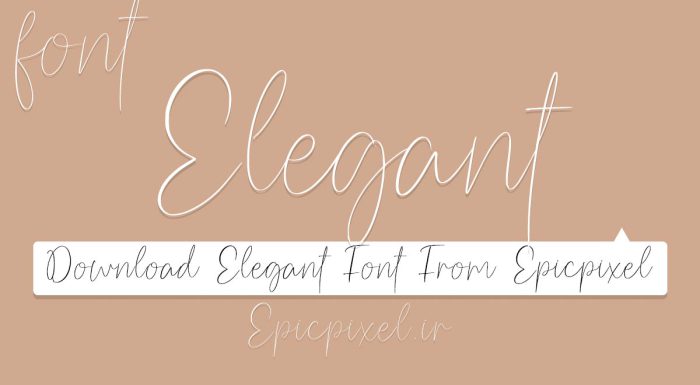
فونت Elegant انگلیسی
دانلود فونت Elegant انگلیسی Font الگانت |
| ⭐ مجموعه فونت | دانلود فونت انگلیسی الگانت Font Elegant |
| ⭐ توضیحات | الگانت یک قلم دست نویس بسیار نرم و تمیز است که بسیار فریبنده است و توجه بسیاری از افراد را به خود جلب می کند. و مناسب برای کسانی از شما که به فونت برای بسته بندی محصول، پروژه های برندسازی، مجلات، عکاسی واترمارک نیاز دارند. رسانه های اجتماعی، عروسی، کارت ها، دعوت نامه ها و خیلی بیشتر! |